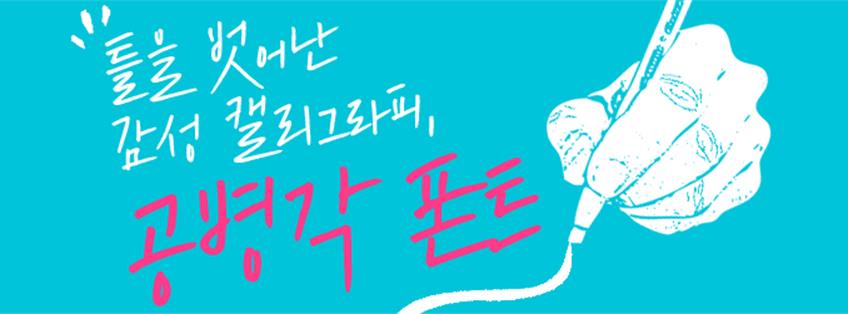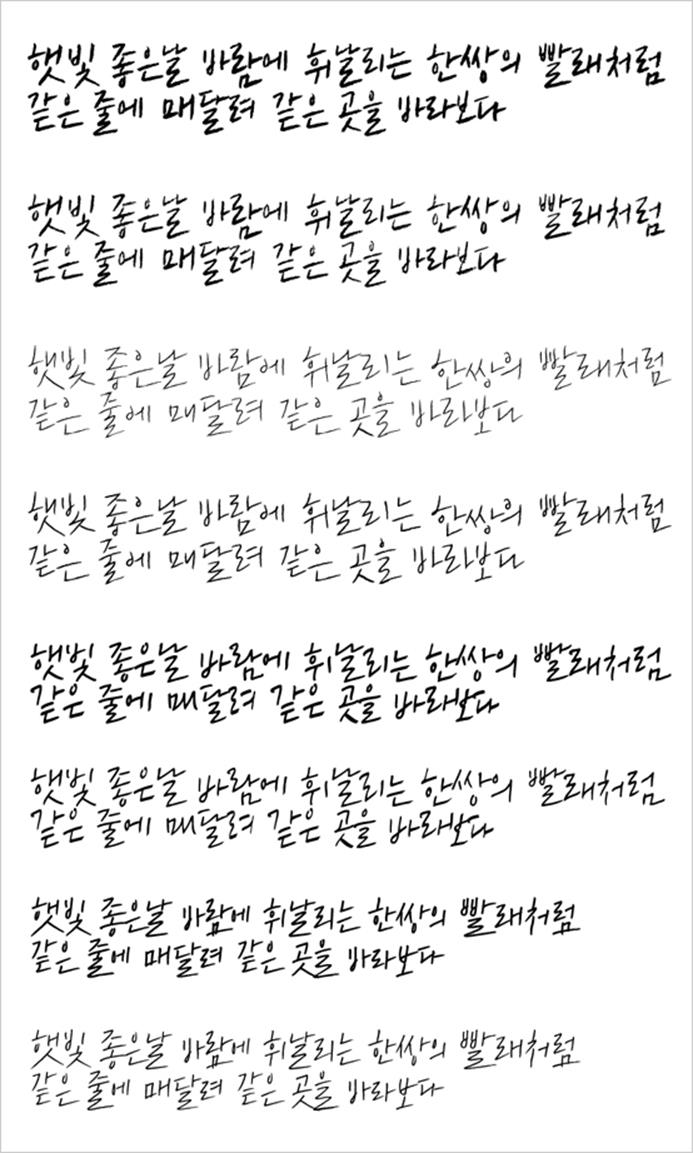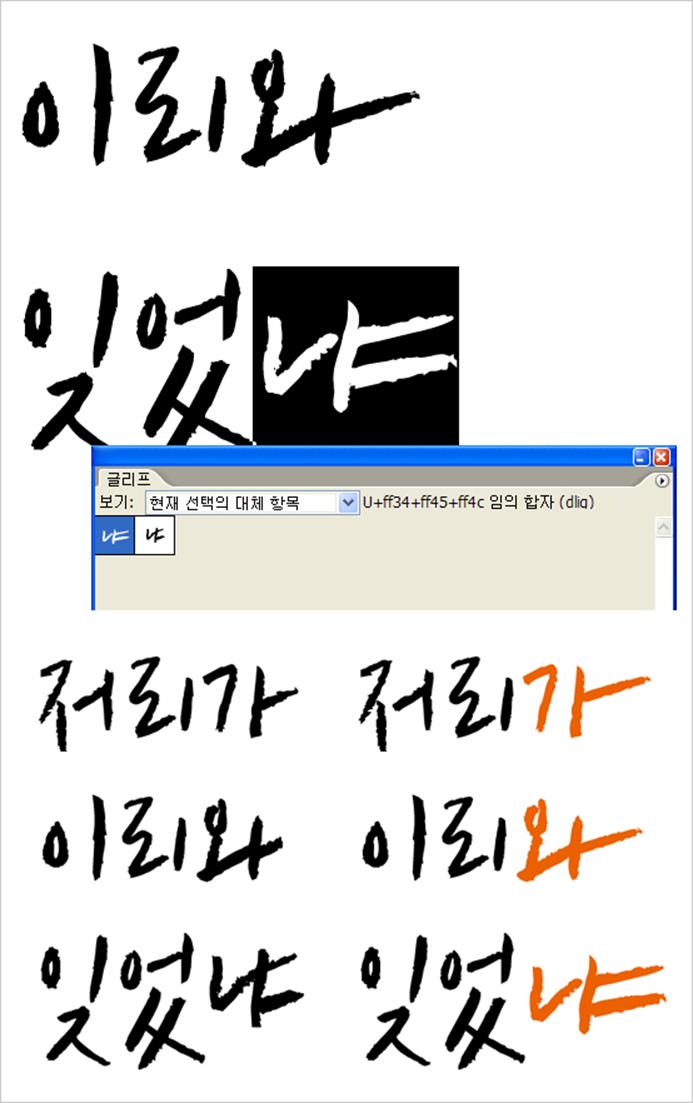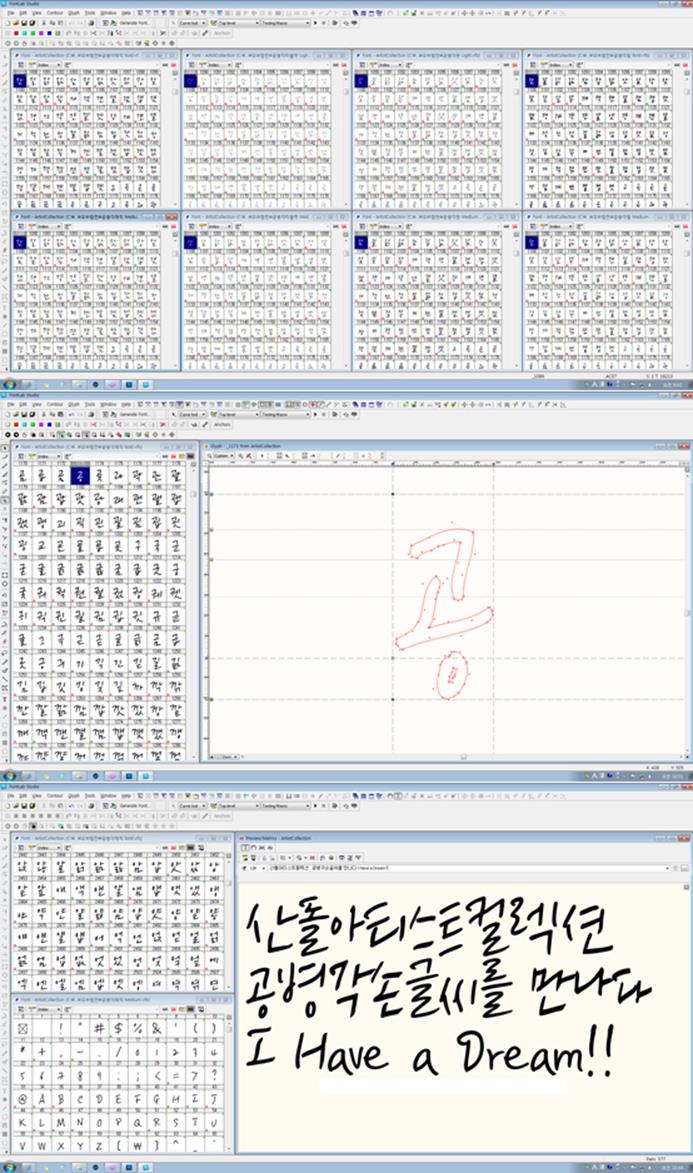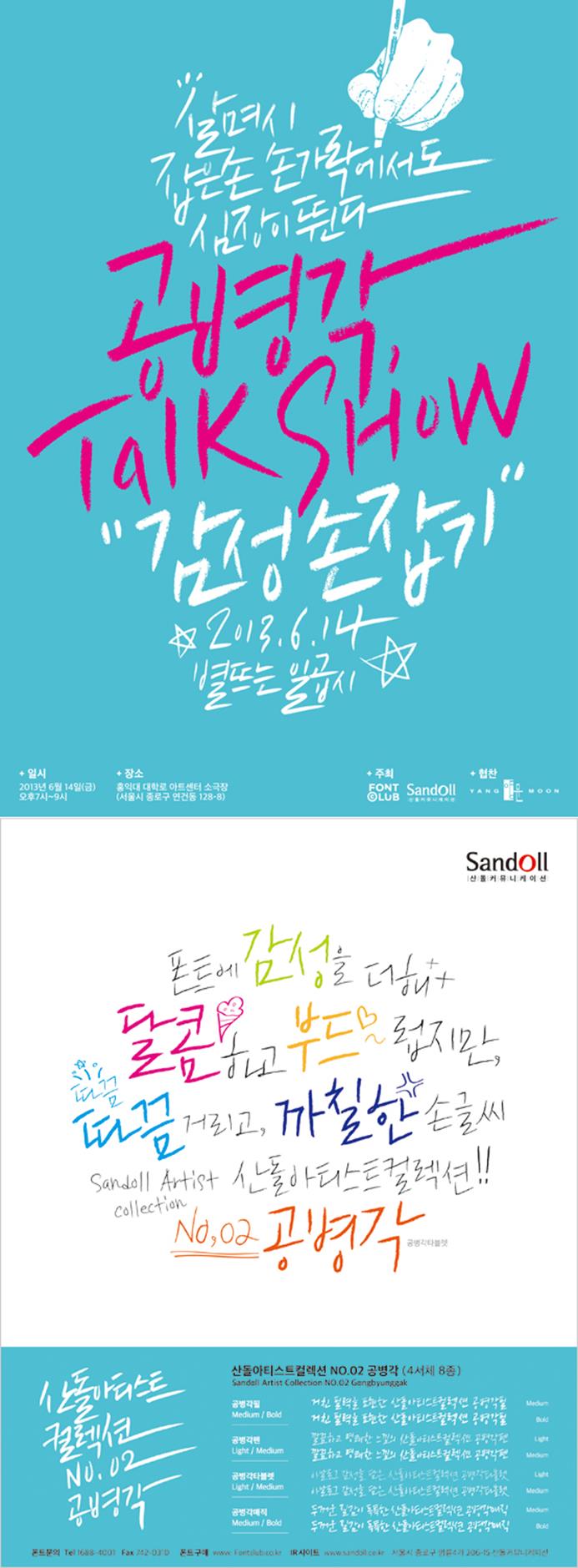
틀을 벗어난 감성 캘리그라피, 공병각 폰트
소문만 무성했지 폰트로는 만나보기 어려울 것 같았던 공병각 작가의 손글씨가 폰트로 만들어졌다. 공병각 폰트는 과거에 비해 다양해진 사용 환경과 사용자들의 다양한 감성을 고려해 사인펜, 색연필, 타블렛, 매직 등 네 종류의 손글씨 폰트로 개발되었다. 곽두열 산돌커뮤니케이션 폰트디자인팀 팀장과 이호 닥터폰트 실장(전 산돌커뮤니케이션 폰트디자이너)의 도움으로 공병각 폰트 개발 과정에 대한 이야기를 들어보았다.
먼저, 공병각 폰트 소개를 부탁 드릴게요.
잘 아시겠지만, 공병각 작가는 다양한 광고 작업을 비롯해 앨범과 단행본, 기업 콜라보레이션 작업 등에 개성 강하고 감성 어린 손글씨를 선보이며 많은 사랑을 받고 있는 캘리그라퍼이자 아티스트이죠. ‘공병각 폰트’는 공병각 작가님(www.cyworld.com/NEMAM22DA)의 손글씨를 디지털 폰트로 제작한 손멋글꼴입니다. 석금호펜, 석금호필, 백종열펜, 백종열필, 박효진, 쌈지농부이진경 등의 손멋글꼴이 포함되어 있는 첫 번째 산돌아티스트컬렉션에 이어 두 번째로 출시되는 패키지 제품이죠. 정식 명칭은 ‘산돌아티스트컬렉션 NO.02 공병각’입니다. 공병각매직(Medium, Bold), 공병각타블렛(Light, Medium), 공병각펜(Light, Medium), 공병각필(Medium, Bold) 등 4서체 8종으로 제작되었고요. KS완성형 TTF와 OTF로 개발되었습니다.
공병각 작가가 참여한 앨범과(위) 직접 쓰고 디자인한 단행본(아래)
공병각 폰트의 가장 큰 특징은 무엇인가요?
공병각 폰트는 개성 강한 필체로 그 동안 다양한 캘리그라피 작업을 해온 공병각 작가 손글씨의 아날로그 감수성을 디지털화한 것인데요. 공병각 폰트를 이용해 어렵지 않게 사용자들의 감성과 메시지를 전달할 수 있도록 제작했습니다. 공병각 폰트의 가장 큰 특징이라면, 기존 산돌아트스트 컬렉션 폰트와는 다르게 사인펜, 색연필, 타블렛, 매직 등 풍부한 필기감과 다양한 종수를 제공한다는 점입니다. 또한 모음 ‘ㅏ’, ‘ㅑ’, ‘ㅘ’ 계열에 임의합자(ligature) 기능(멀티글립 기능)을 제공해 공병각 작가만의 개성 있는 손글씨를 보다 다양하게 연출할 수 있도록 했습니다.
위에서부터 공병각필(Bold, Medium), 공병각타블렛(Medium, Light), 공병각매직(Bold, Medium), 공병각펜(Medium, Light)
공병각 폰트의 멀티글립 기능 예시. 글자 위치에 따라 적절한 손글씨 느낌을 부각시킬 수 있다. 인디자인과 일러스트레이터 CS버전 이상에서 적용 가능하다.
공병각 폰트 개발은 어떻게 이루어졌나요?
이미 공병각 작가님과 그분의 캘리그라피 작업에 대해서는 잘 알고 있었어요. 백종열체와 박효진체 이후에 작가 이름을 그대로 살린 산돌의 작가 폰트 개발을 준비하며 자료 조사를 꾸준히 해오고 있었거든요. 그 중에서도 공병각 작가님은 산돌에서 폰트 개발을 제안하고자 했던 작가 중 한 분이었죠. 그 즈음에 공교롭게도 공병각 작가님이 먼저 산돌에 연락을 주시고 폰트 개발을 문의해 오셨습니다. 그때부터 큰 문제 없이 공병각 작가님과 폰트 제작을 위한 작업이 이루어졌죠. 처음엔 폰트로 제작할 계획이 없었는데, 점차 폰트 제작에 대한 문의도 많아지고 공병각 작가님 스타일을 어설프게 따라 한 작업들이 많아지면서 공병각 폰트를 제작할 시점이 되었다는 판단으로 폰트화를 결심하셨다고 합니다.
복잡한 여러 단계가 있지만, 간단히 설명을 드리면 4단계 정도로 정리되겠네요. 가장 먼저 작가 원도를 확보해야겠죠. 폰트를 제작할 때 필요한 모듈이 포함된 샘플 텍스트 500여자를 제공해드리면 필기구에 따라 작가분이 샘플 텍스트를 직접 써주시는 과정입니다. 2단계는 작가 원도를 스캔해 디지털 이미지화 하고 벡터 형식으로 변화해 모듈이 되는 글자를 확보하는 과정입니다. 그 다음, 모듈을 활용하여 한글 2,350자를 파생합니다. 마지막으로, 완료된 글립을 활용해 조판테스트를 진행하고 사용에 문제가 없는지 검수하고 수정합니다.
다양한 도구와 방식으로 쓰여진 캘리그라퍼 공병각 작가의 손글씨 원도 일부.
산돌 손글씨 폰트만의 특징은 무엇인가요?
이번 공병각 폰트 작업도 그랬지만 산돌에서 제작하는 손글씨 폰트의 가장 큰 특징은 작가의 손글씨 스타일을 최대한 살리기 위해 노력하고 있다는 점입니다. 당연한 이야기로 들릴 수 있겠지만, 작가의 손글씨 원도를 얼마나 많이 가져와 작업을 하느냐에 따라 느낌이 달라질 수 있습니다. 손글씨 원도가 적을수록 폰트디자이너의 생각과 스타일이 개입될 여지가 많아지는 것이죠. 작업을 하다 보면 폰트디자이너가 좋아하고 편한 스타일로 변형될 수 있어요. 사용자들이 좋아할만한 매끈한 폰트가 만들어질진 몰라도 그 작가의 스타일이 살아있는 손글씨 폰트와는 거리가 멀어질 수 있죠.
산돌에서는 대체적으로 한글, 라틴알파벳, 약물이 포함된 500~600자 정도의 원도를 작가에게 요청 드리고 폰트디자이너가 중복되는 글자를 포함해 파생 작업을 진행하게 됩니다. 이번 공병각 폰트 또한 사인펜, 색연필, 타블렛, 매직 등 다양한 도구로 쓴 원도를 최대한 많이 받아 모두 개별적으로 제작되었습니다. 산돌에서 요구하는 원도 분량이 다소 많아 작가분들이 다소 힘들어하시리라 짐작되지만, 그렇게 해야 산돌에서 제작하는 손글씨 폰트만의 자연스러움과 작가다움을 살릴 수 있기 때문에 작가분들에게 이해를 구하고 있습니다.
공병각 폰트 작업창과 공병각매직 조판테스트 화면
제작 과정 중에 어려움은 없었나요?
공병각 폰트 제작 과정 중에 특별히 어려움은 없었어요. 폰트 제작 과정 중 어려운 점이라고 한다면, 모든 작가 폰트가 그러하듯이 원작자 원도 느낌을 그대로 잘 살리기 위한 노력과 시간에 있겠죠. 500여자가 되는 샘플 텍스를 바탕으로 폰트디자이너가 나머지 1,800여자를 만들어야 하는데 상당 부분 폰트디자이너가 작업하게 됩니다. 이 과정이 가장 어렵고 많은 시간을 요하는데요. 전체적인 조화와 자연스러움, 폰트의 완성도를 위해서는 작가의 필력, 필획의 순서 등을 충분히 파악하고 학습한 뒤에 본격적인 제작에 들어가야 합니다. 꾸준히 많은 사랑을 받고 있는 백종열체도 그렇게 제작되었습니다.
공병각 폰트와 백종열 폰트의 다른 점은 무엇인가요?
지금은 각자의 영역에서 활동하고 계시지만, 오래 전 공병각 작가님과 백종열 감독님은 같은 회사에서 7년 이상 광고 작업을 하셨는데요. 오랜 기간 함께 일하고 작업을 하면 자연스럽게 서로 영향을 주고 받을 수 밖에 없습니다. 하지만 두 분 모두 꾸준히 그들만의 영역에서 스타일을 만들고 발전시켜왔기 때문에 엄연히 필체도 다르고 폰트도 다릅니다. 큰 틀 안에서는 얼핏 유사한 느낌으로 다가올 수 있지만, 백종열체는 남성스럽고 강한 느낌이 풍기는 반면, 공병각 폰트는 그보다는 여성스럽고 부드럽게 느껴집니다.
그리고 무엇보다, 공병각 폰트는 틀을 벗어나는 형태가 굉장히 많아요. 한글에는 글자가 들어가는 고정 폭이 있는데 공병각 폰트는 그 범위가 넓은 편입니다. 그 점이 공병각 폰트의 가장 큰 멋스러움과 재미 요소 중 하나이기 때문에 그 부분을 최대한 살릴 수 있도록 작업했습니다. 공병각 폰트에서는 다양한 필기감을 구현할 수 있다는 점도 큰 차이겠죠.
공병각 캘리그라퍼가 직접 쓴 손글씨로 제작한 <공병각 Talk Show> 포스터(위)와 공병각 폰트로 제작한 광고 이미지(아래)
공병각 폰트가 어떻게 사용되길 바라나요?
가끔 대형서점에 나가 나눔손글씨나 백종열체로 작업한 책 표지를 보면 “어딘지 모르게 약하다”는 느낌을 받곤 합니다. 물론, 모든 작업이 그렇지는 않지만 아마도 손글씨 폰트를 본문체 사용하듯 입력한 그대로 작업하거나 장평이나 자간 조절만 해서 그런 것 같아요. 그래서는 손글씨만의 매력과 장점을 살리기 어렵겠죠. 이미지 크기와 레이아웃을 고민하듯 손글씨를 사용할 땐 어느 정도 가공이 필요한데요. 공병각 폰트도 비슷합니다. 굵기나 컬러, 레이아웃 등을 한번쯤 고민하고 다듬어주어야 좋습니다. 공병각 작가님이 손글씨도 쓰고 직접 디자인한 단행본들이 많이 나와있기 때문에 공병각 폰트를 사용할 때 참고자료로 활용이 가능합니다. 이 점도 공병각 폰트만의 가장 큰 강점이자 특징이 될 수 있겠네요. 부디, 공병각 폰트만의 매력을 한껏 뽑아낼 수 있길 바랍니다.